media【初心者向け🔰】デザインにおけるフォントとイラストの相性
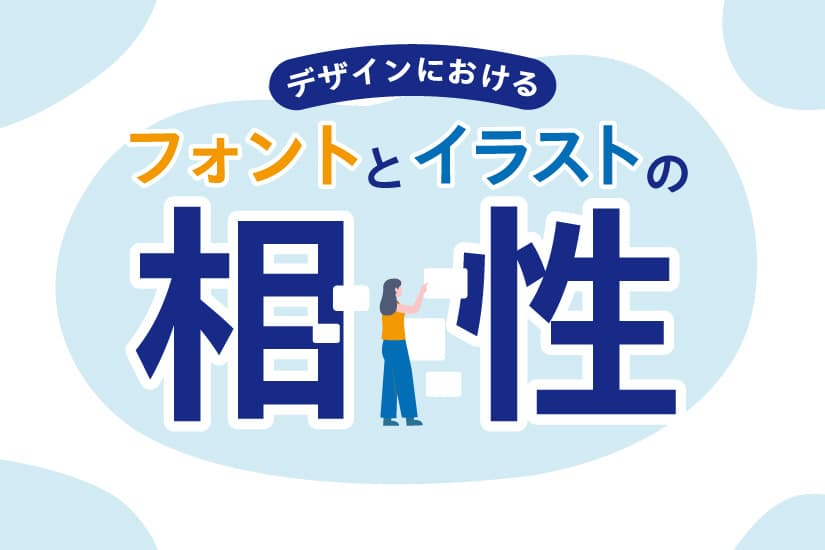
今回はデザインにおけるフォントとイラストの相性について解説していきたいと思います。
はじめに
デザインをするにあたり、イラストとテキストを組み合わせることは多いですよね。
今は無料のイラストを配布しているサイトも多いため、組み合わせるだけで誰でも簡単にバナーやチラシなどのデザイン作成ができます。
ただし、とりあえず闇雲にイラストとテキストを組み合わせれば良いデザインになるとも限りません。
そこで、本記事ではデザインの質に繋がるフォントとイラストの相性をテーマに解説していきたいと思います。
フォントとの組み合わせによって変わる印象
以下2つのデザインをご覧ください。
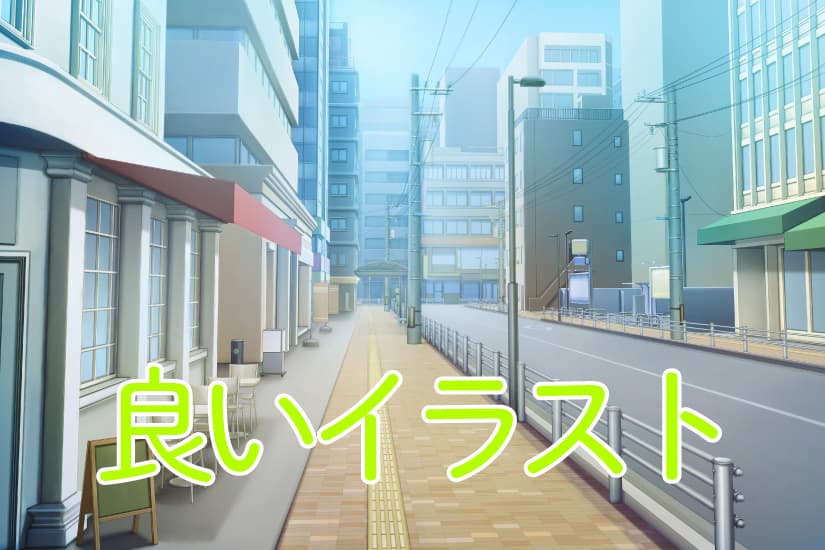
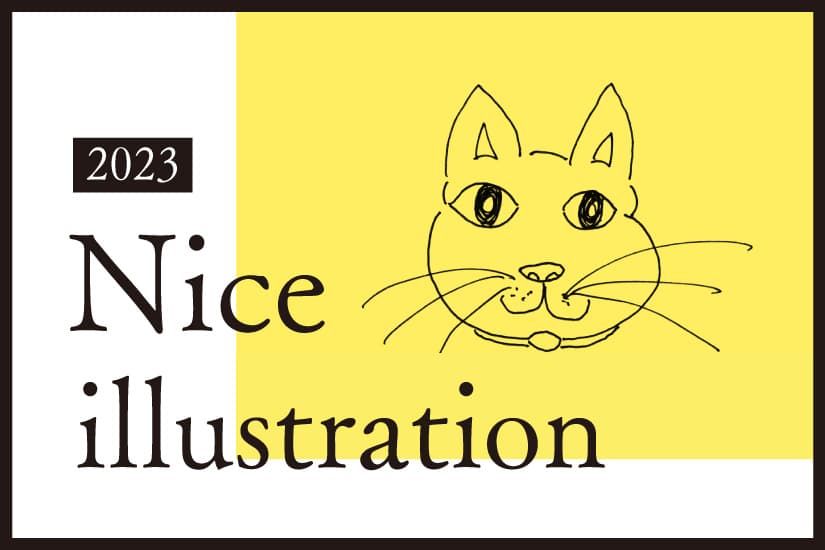
左上は綺麗めな風景イラストではありますが、丸ゴシックのフォントと組み合わせて見た時に急にチープな印象になります。
その一方で右上のイラストは一見チープに見えますが、セリフ体の英字フォントと組み合わせて見た時に、何となくオシャレな印象になります。
このように、イラストとフォントの組み合わせ方によって与える印象は大きく変わります!
フォント別!一緒によく用いられるイラストの種類
ということで、フォント毎に一緒によく使われるイラストの例をまとめてみました。
ゴシック体
ゴシック体×フラット
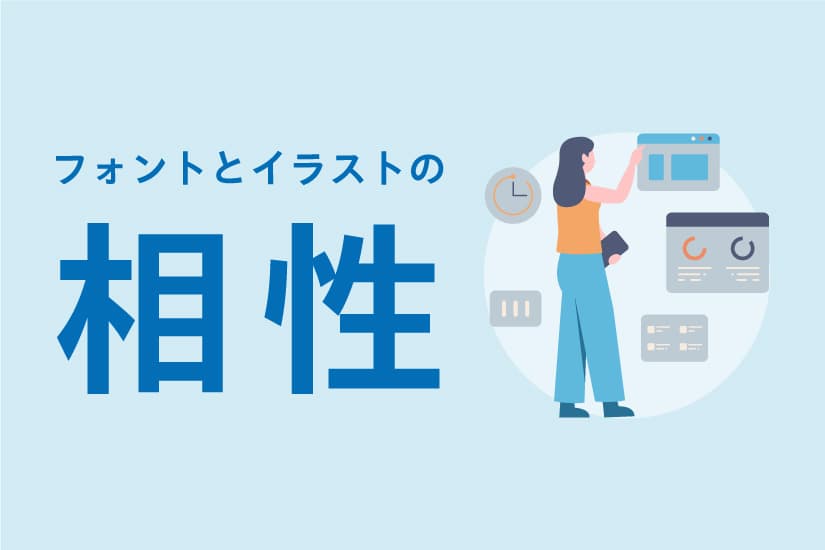
ゴシック体とフラットイラストの組み合わせが、ウェブデザインでは最もよく見かけるものの一つです。視認性も抜群なので汎用性も高いデザインです!
ゴシック体×アイソメトリック
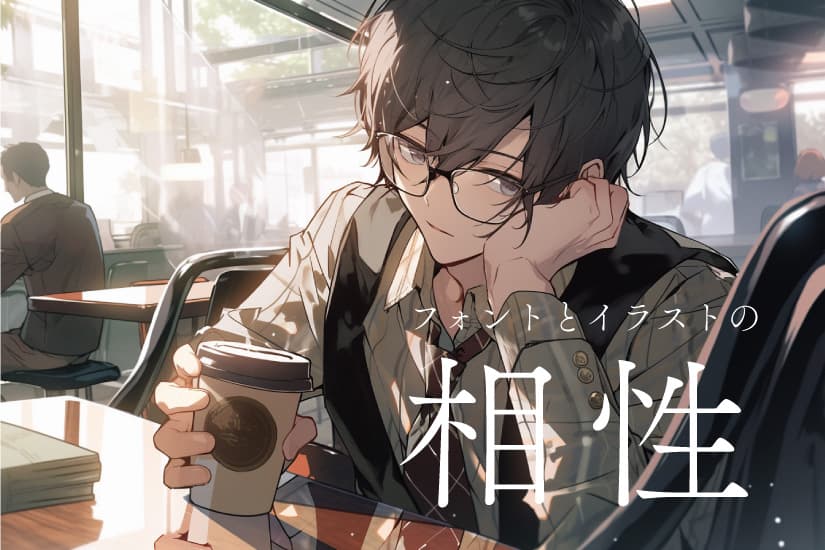
3D表現でゴシックとの相性が抜群のイラストタイプ。フラット以上にスタイリッシュな印象が高まるため、ゴシック系以外のフォントは逆に使いにくいです。ちなみに、背景やパーツなどでグラデーションがよく使われます。
ゴシック体×コミック調
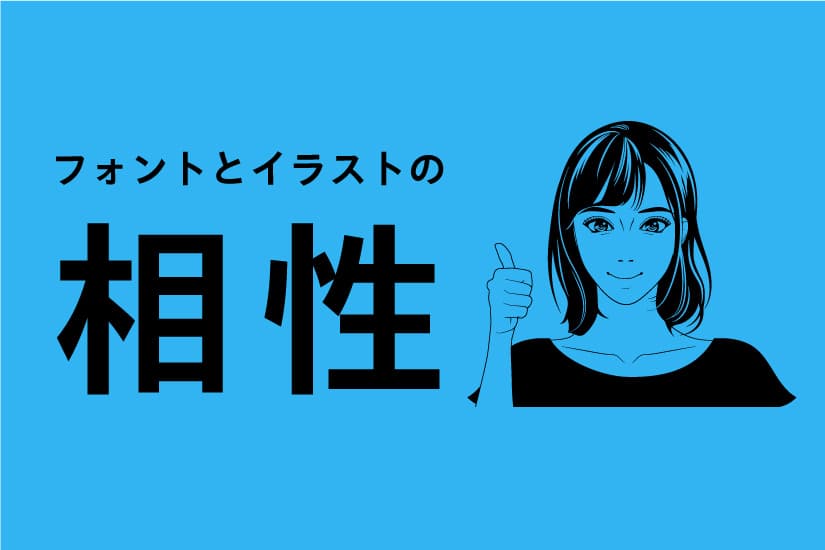
さらに、ゴシックはコミック風の単色でコントラストがはっきりしたイラストとの相性も良いです。ブックデザインなどDTPの分野で特に多く見かける印象です。
丸ゴシック体
丸ゴシック体×ラインアート
いわゆる線画です。これもウェブデザインでフラットと同じくらいよく見かけるイラストタイプです。そして、必ずといって良いほど丸ゴシック体と一緒に使われています。それくらい相性が良いということですね。
丸ゴシック体×手描き風
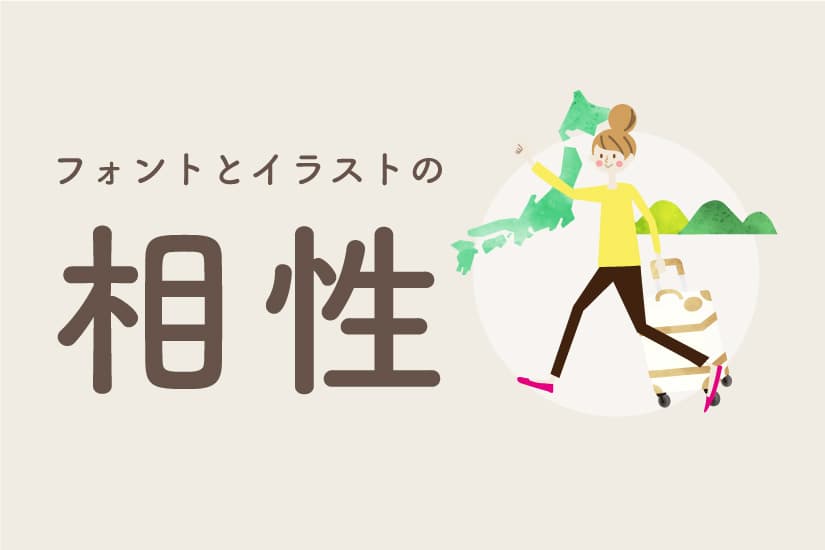
最近ではウェブデザインの領域でも手描き風のイラストが使われることが多くなってきています。ここでもやはり丸ゴシック体が使われていることが多いです。イラストと相まって柔らかく優しい印象を与えます。
明朝体
明朝体×手描き風
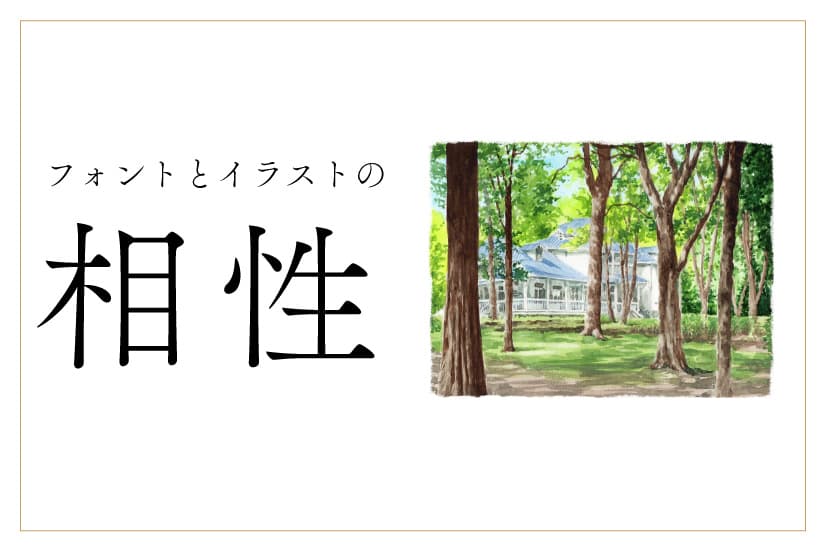
明朝体とイラストの組み合わせはゴシック体ほど多く見かけることはないですが、より繊細なアート作品のような絵と一緒に使われることがあります。絵画展のポスターとかには明朝体が使われることが多い印象です。
明朝体×アニメ風
意外かもしれませんが明朝体はアニメ風のイラストにもよく使われています。ライトノベルのデザインなどでこの組み合わせはよく見かけますね。
トレンドを参考にしつつ日々研究を
本記事では分かりやすさを考慮して書体を大きく3つに分けましたが、厳密にはもっと細かく存在するため、イラストとの相性をそのフォント毎に考える必要があリます。
また、元のフォントをアレンジしてタイポグラフィーとして、イラスト と組み合わせるケースも多いです。
必ずしもこれを使わないといけないという決まりはないので、最近のトレンドを参考にしつつ、その都度デザインに最適な組み合わせを見つけていくと良いでしょう!
まとめ
いかがでしたでしょうか。
このようにフォントとイラストの組み合わせ次第でデザインが与える印象は大きく変わるので、デザイン制作の上でぜひ参考にしてみてくださいね。
ちなみに、イラストとフォントの相性以外の面でデザインの質を上げる要素は他にもあるので、探してみても良いかと思います。